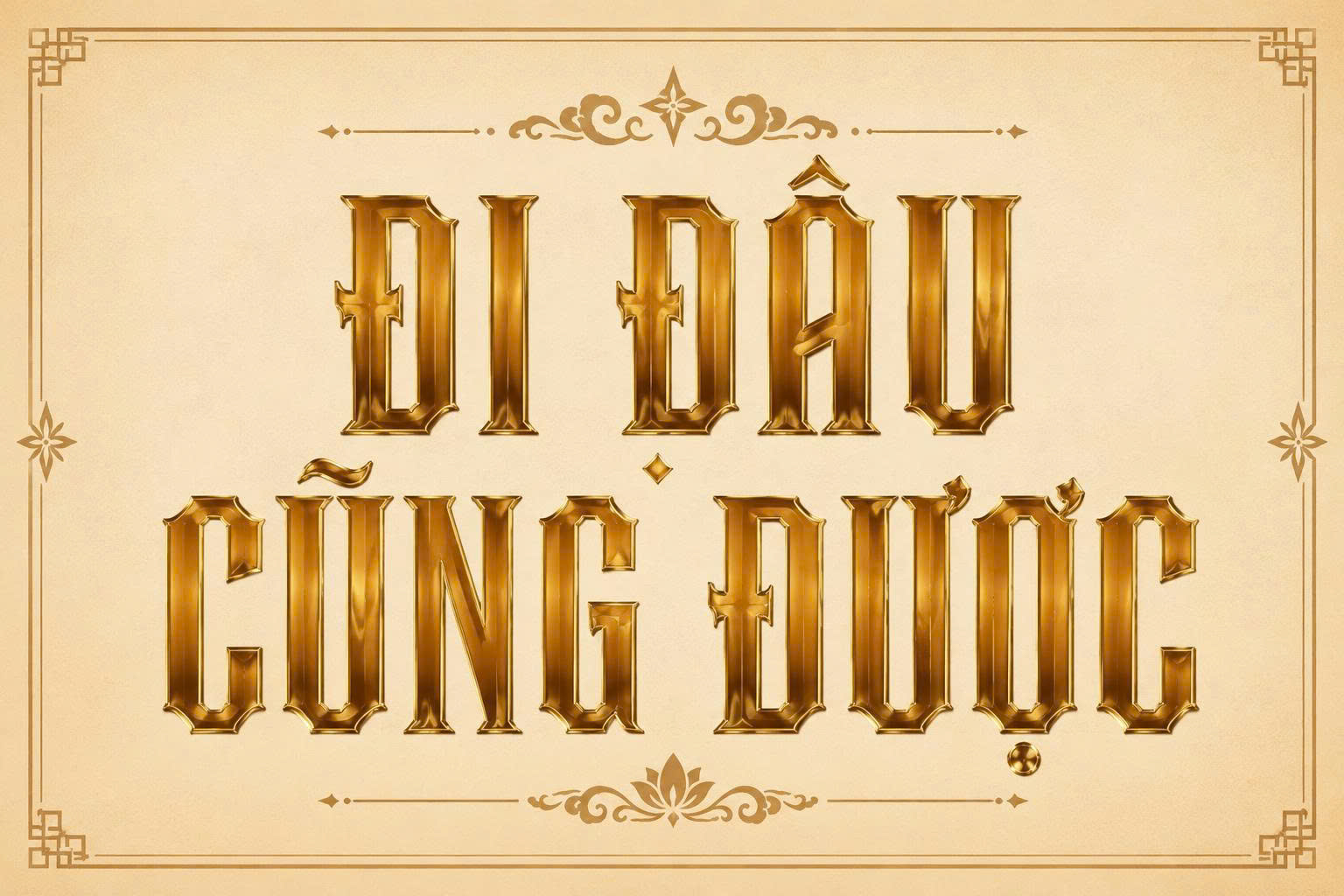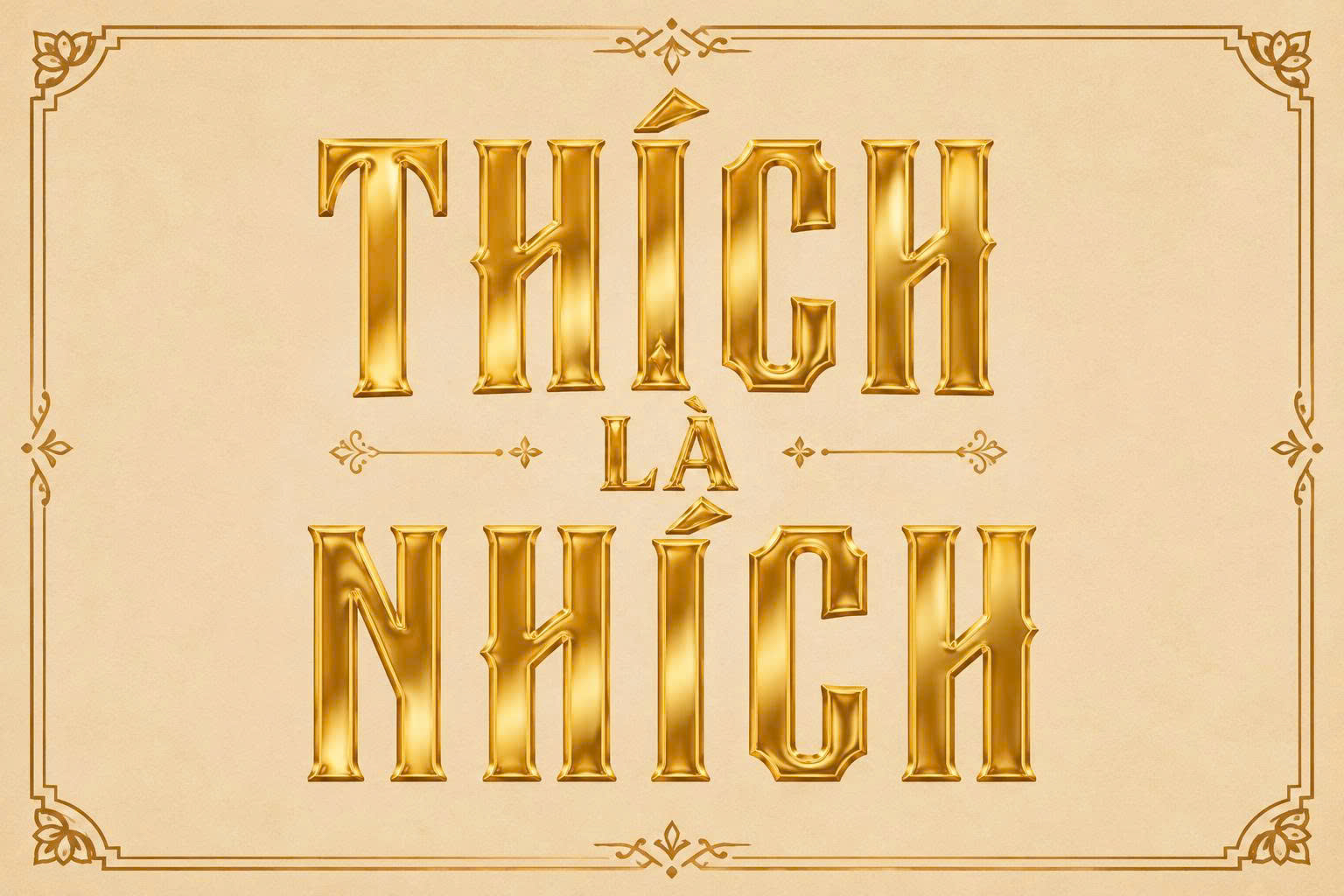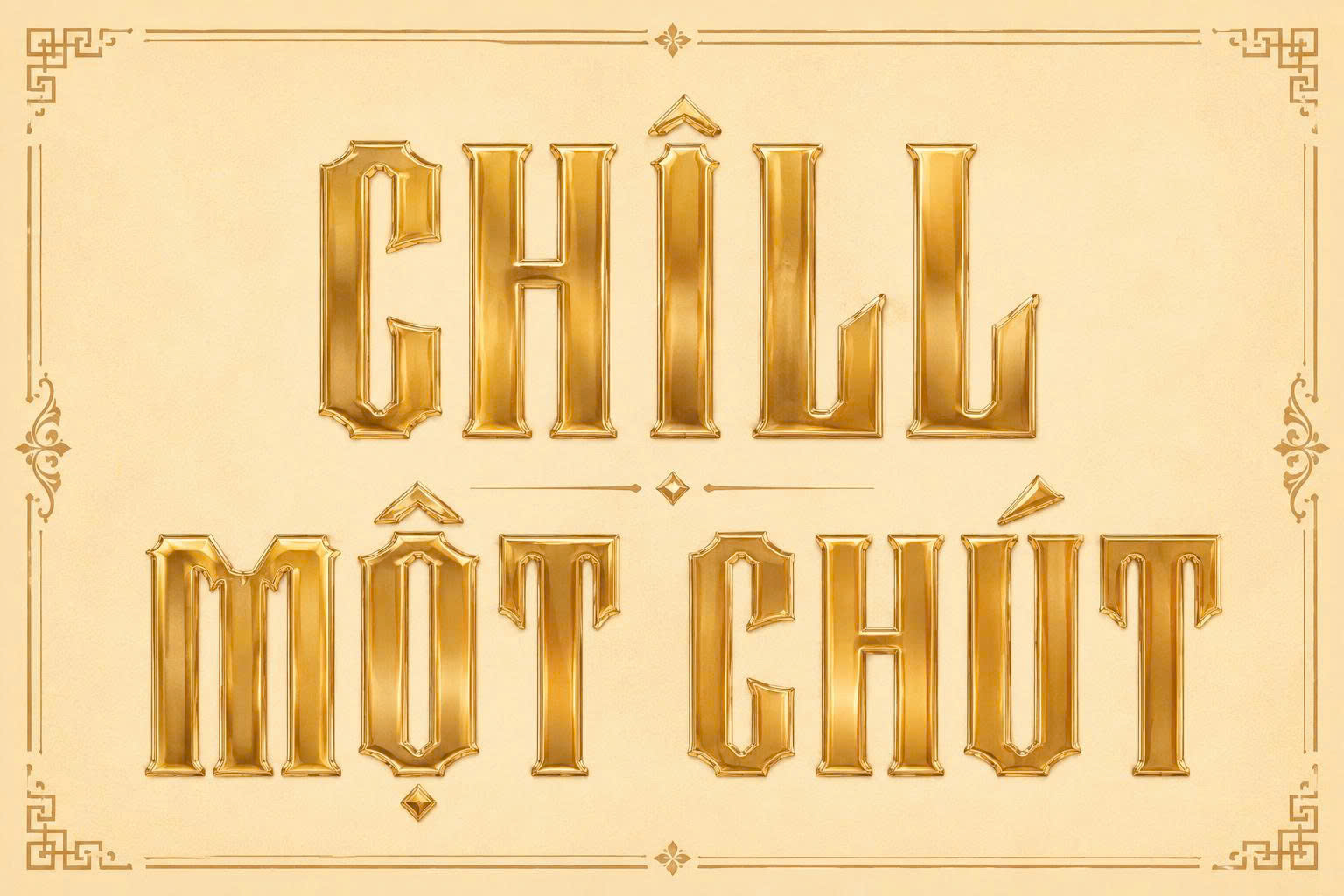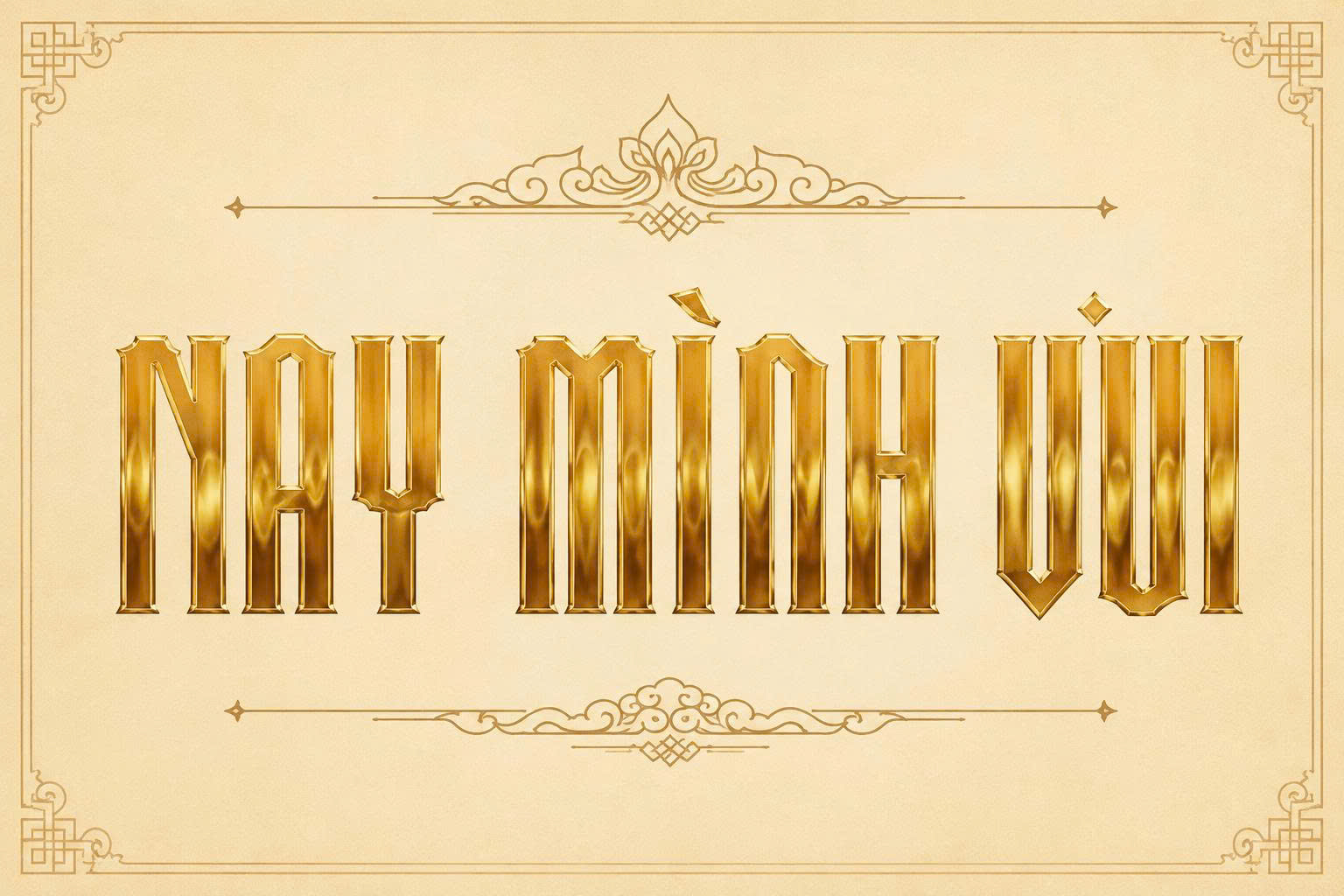
Font chữ lịch sử Việt hóa là nhóm các phông chữ được thiết kế dựa trên các tư liệu văn hóa cổ như mộc bản Triều Nguyễn, văn bia, sắc phong hoặc các ấn phẩm báo chí, bảng hiệu vẽ tay đầu thế kỷ 20. Khác với các dòng font hiện đại, font chữ mang phong cách lịch sử giúp các bản thiết kế bao bì, bìa sách và nhận diện thương hiệu toát lên vẻ uy nghi, truyền thống và đậm đà bản sắc dân tộc. Doozypack.vn chia sẻ link tải bộ font lịch sử Việt hóa chuẩn, giúp bạn giải quyết triệt để lỗi dấu tiếng Việt khi thực hiện các dự án hoài cổ.
Font chữ lịch sử Việt hóa là gì và tại sao nên sử dụng?
Việc sử dụng một bộ phông chữ đúng ngữ cảnh lịch sử không chỉ giúp bản thiết kế đẹp hơn mà còn thể hiện sự am hiểu và tôn trọng đối với giá trị văn hóa xưa.
Mẫu chữ phong cách lịch sử
Tái hiện không gian văn hóa qua từng nét chữ
Đặc trưng lớn nhất của font việt hóa lịch sử là cấu trúc nét chữ mô phỏng lại các kỹ thuật thủ công thời xưa như khắc gỗ (mộc bản), đục đá (văn bia) hoặc viết bút lông đẫm mực. Những chi tiết như nét xước tự nhiên, độ dày mỏng không đồng đều tạo nên một cảm xúc hoài niệm mãnh liệt, giúp khách hàng cảm nhận được chiều sâu câu chuyện mà thương hiệu muốn truyền tải.
Giải quyết nỗi đau lỗi dấu trên phông chữ cổ phong
Nhiều designer thường tìm thấy các bộ font phong cách Á Đông rất đẹp nhưng lại bị lỗi nhảy font hoặc sai lệch vị trí dấu thanh (sắc, huyền, hỏi, ngã, nặng) khi gõ tiếng Việt. Bộ sưu tập tại Doozypack.vn đã được tinh chỉnh bộ dấu chỉn chu, đảm bảo các ký tự như “ơ, ư, đ” luôn đồng nhất với phong cách nghệ thuật của bộ font gốc, giúp thành phẩm in ấn luôn chuyên nghiệp.
Kiểu chữ cổ điển ấn tượng
Các nhóm font lịch sử Việt hóa phổ biến trong thiết kế bao bì
Tùy vào giai đoạn lịch sử và tinh thần sản phẩm, bạn có thể lựa chọn một trong các nhóm phông chữ tiêu biểu sau đây:
• Nhóm font Mộc bản & Văn bia: Nét chữ vuông vức, mộc mạc, mô phỏng lối khắc trên gỗ hoặc đá. Phù hợp làm tiêu đề cho các hộp trà, hộp sâm hoặc thực phẩm truyền thống.
• Nhóm font Báo chí đầu thế kỷ 20: Mang phong cách Tân cổ điển với các nét thanh đậm rõ rệt, thường thấy trên các tờ báo hoặc biển hiệu tiệm may xưa.
• Nhóm font Thư pháp hành thư: Nét bút phóng khoáng, bay bổng, lý tưởng cho các dòng bao bì quà tặng lễ hội như bánh Trung thu, quà Tết.
Gợi ý từ Doozypack.vn: Nếu bạn đang thiết kế bao bì xuất khẩu mang đậm tính Việt Nam, hãy ưu tiên nhóm font lịch sử Việt hóa dòng Sans-serif hiện đại pha chút hoài cổ. Sự kết hợp này giúp bao bì vừa mang hồn Việt, vừa dễ tiếp cận với người tiêu dùng quốc tế.
Ứng dụng của font việt hóa lịch sử trong in ấn tại Doozypack.vn
• Thiết kế hộp bánh Trung thu: Những tiêu đề như “Đoàn Viên”, “Nguyệt Viên” sử dụng font chữ mộc bản in dập nổi trên giấy mỹ thuật đỏ mang lại vẻ đẹp vô cùng uy nghi.
• Nhãn trà và nông sản cao cấp: Sự kết hợp giữa font lịch sử và chất liệu giấy Kraft nâu tạo nên bộ nhận diện thương hiệu mộc mạc, đáng tin cậy.
• Bao bì dược phẩm đông y: Nét chữ nghiêm cẩn của phông chữ lịch sử giúp khẳng định sự lâu đời và uy tín của các bài thuốc gia truyền.
03 Lưu ý kỹ thuật khi in ấn các bộ font mang tính hoài cổ
Việc đưa một phông chữ có nhiều chi tiết xước mộc mạc lên chất liệu giấy đòi hỏi designer cần lưu ý một số vấn đề tại xưởng in chuyên nghiệp:
• Xử lý các chi tiết xước li ti: Font lịch sử thường có hiệu ứng “cũ kỹ” với các mảnh xước mực nhỏ. Khi gia công ép kim (Hot Stamping), các chi tiết này cần được làm mịn bớt hoặc tăng nhẹ độ dày nét để tránh hiện tượng nhũ bị bong tróc.
• Lựa chọn chất liệu giấy: Nhóm font này phát huy tối đa vẻ đẹp khi in trên các loại giấy có bề mặt nhám như giấy Kraft, giấy Ivory cán mờ hoặc giấy mỹ thuật có gân. Tránh dùng giấy quá bóng vì sẽ làm mất đi cảm giác “mộc” đặc trưng.
Thiết kế chữ mang hơi hướng xưa